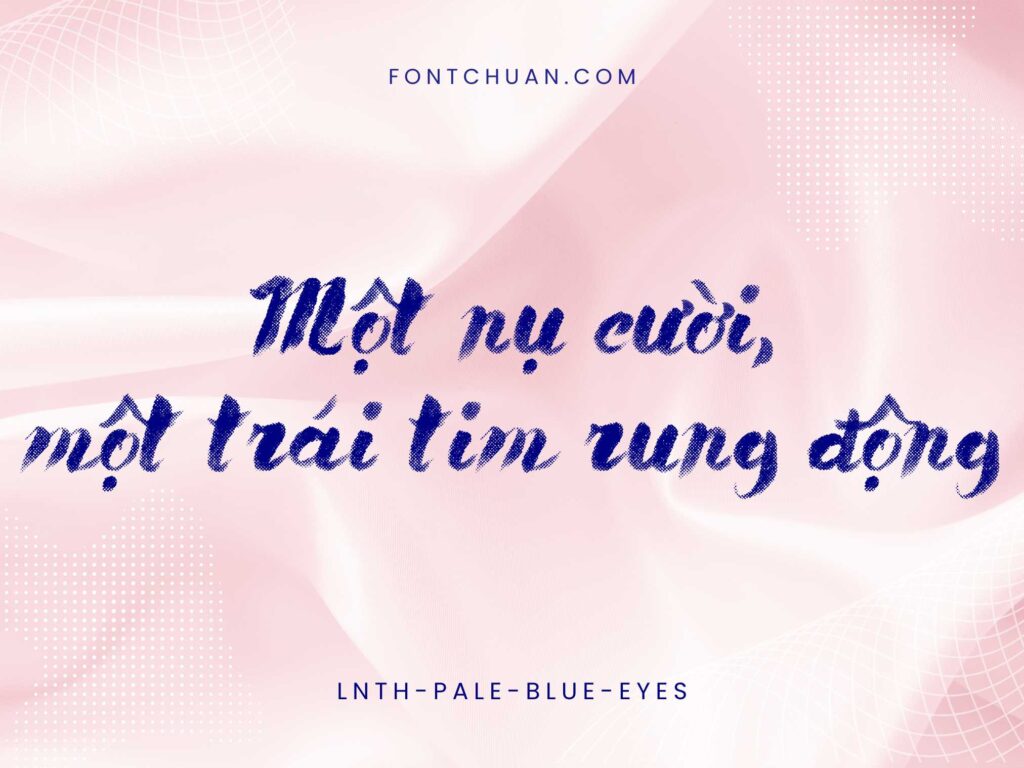
Font LNTH Pale Blue Eyes Việt Hóa
Font Pale Blue Eyes là một kiểu chữ viết tay mang phong cách nhẹ nhàng, tinh tế và thanh thoát. Với các đường nét mềm mại, font này mang đến cảm giác thư giãn, phù hợp cho các thiết kế mang phong cách tối giản, nghệ thuật hoặc các nội dung cần sự sang trọng, tinh tế. Đây là sự lựa chọn lý tưởng cho các dự án thương hiệu, bao bì sản phẩm, thiệp mời hoặc thiết kế mang phong cách vintage
Phiên bản này đã được Việt hóa bởi LNTH, hỗ trợ đầy đủ tiếng Việt cùng hơn 50 ngôn ngữ khác, giúp người dùng dễ dàng ứng dụng trong thiết kế quốc tế. Font Pale Blue Eyes được các thành viên Font Chuẩn sưu tầm và đăng tải nhằm mang đến một kiểu chữ mềm mại, thanh lịch dành cho những ai yêu thích sự tối giản nhưng vẫn đậm chất nghệ thuật
Về đặc điểm thiết kế, Pale Blue Eyes có các nét chữ mềm mại, hơi nghiêng nhẹ, tạo cảm giác tự nhiên và gần gũi. Kiểu chữ này rất phù hợp để sử dụng trong typography nghệ thuật, thư mời, thiệp cưới, thiết kế logo hoặc các ấn phẩm truyền thông mang phong cách cổ điển
Font Pale Blue Eyes được ứng dụng rộng rãi trong các sự kiện như thiệp cưới, Valentine hoặc các thiết kế mang phong cách trang nhã. Nó phù hợp với nhiều ngành nghề như quảng cáo, spa, ẩm thực, giáo dục